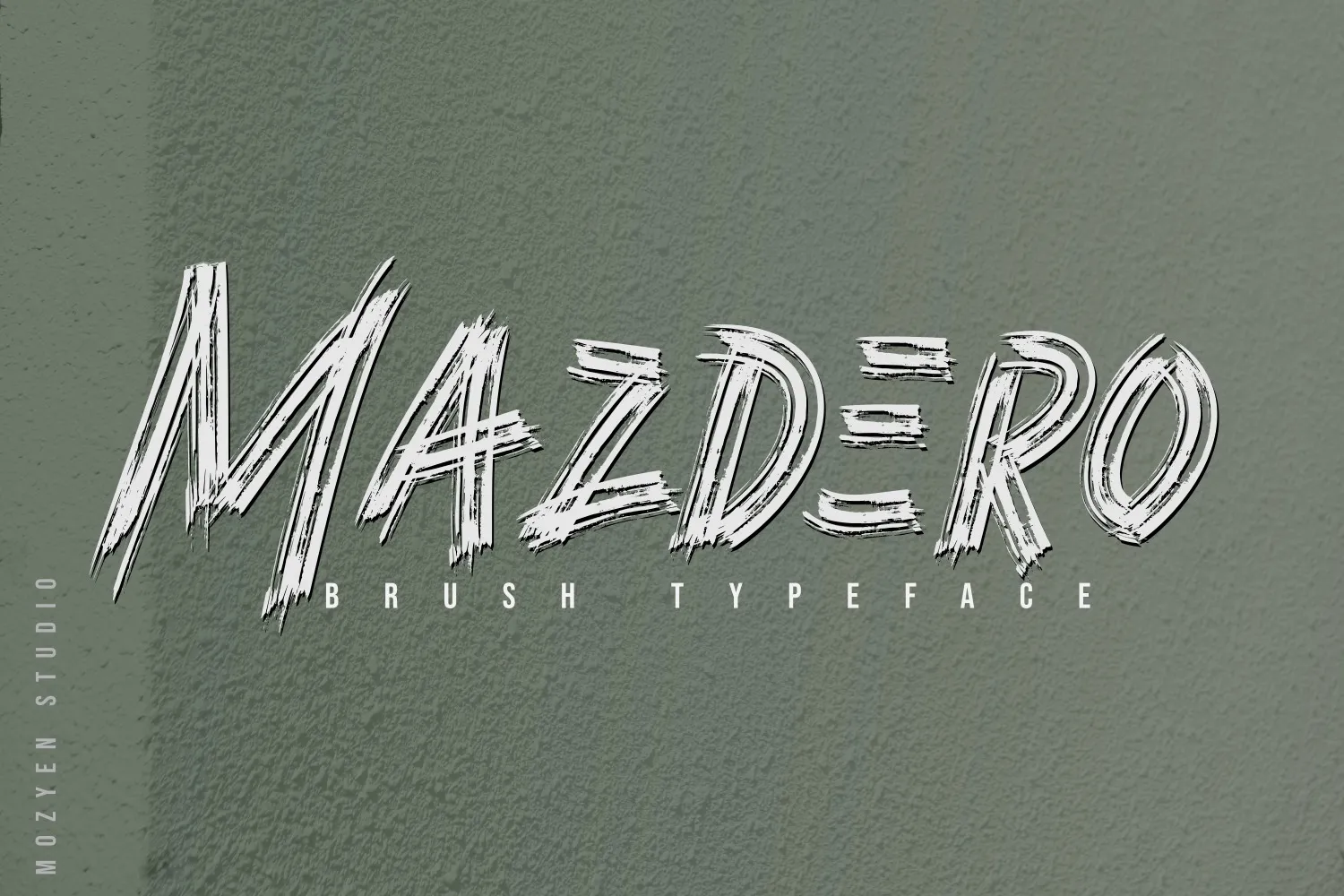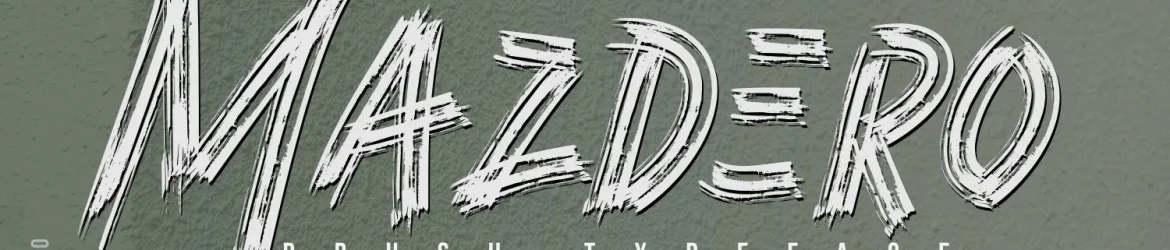
A Mazdero Font é uma tipografia moderna com aspecto de pincel que foi criada pelo designer mozyenstudio, trazendo um toque autêntico e descontraído. Esta fonte foi meticulosamente desenvolvida para aperfeiçoar a combinação de cada característica, tornando-a ideal tanto para projetos gráficos profissionais quanto para expressões artísticas mais criativas. Perfeitamente adaptável para uso em criações como identidade corporativa (Branding), desenho de logotipos (Logo Design), letras e logotipos (Lettering/Logotype), design de roupas, postagem de anúncios, revistas, embalagens, cartazes publicitários, sacolas de shopping, camisetas, capas de livros, fotografia, eventos especiais e outros projetos gráficos. Com seu moderno e autêntico estilo, a Mazdero Font é uma escolha perfeita para quem procura um visual ousado e único em seus trabalhos design.